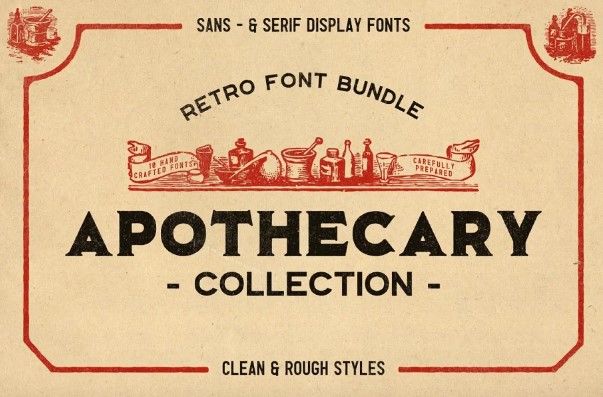
Creativemarket The Apothecary Collection Font
[Creativemarket] The Apothecary Collection Font
Несколько месяцев назад я думал о создании нескольких шрифтов, которые бы соответствовали друг другу.
После нескольких недель напряженной работы "Коллекция аптеки" поступила в продажу.
Все шрифты вдохновлены винтажными лекарствами и книгами фармацевтов, этикетками и вывесками.